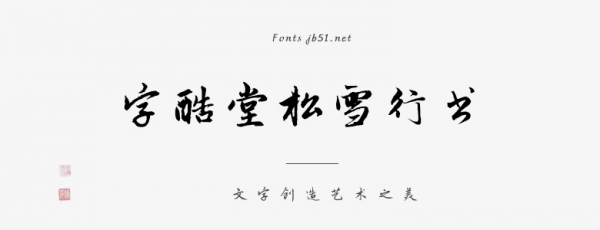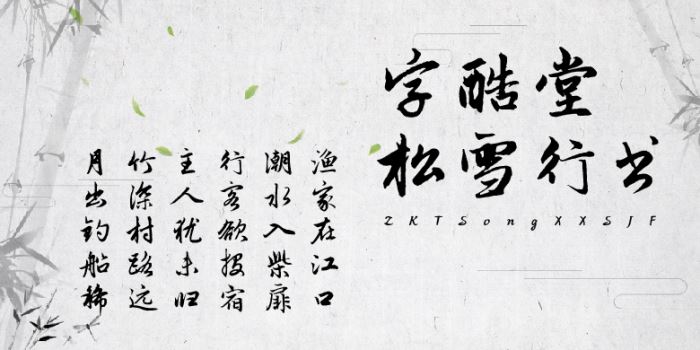
字酷堂松雪行书
字酷堂松雪行书由方正字库过中运设计师出品的艺术字体,该字源自元代书法家赵孟頫的行书书法作品,并根据其书风补上了缺字及简体部分,,适合应用于艺术设计、平面宣传设计、网页设计,书法等领域。
字体介绍
字体源自元代书法家赵孟頫的行书书法作品,并根据其书风补上了缺字及简体部分,赵孟頫博学多才,能诗善文,工书法,精绘艺,擅金石,通律吕,解鉴赏,尤其以书法和绘画的成就最高。在绘画上,他开创元代新画风,被称为“元人冠冕”;赵孟頫亦善篆、隶、真、行、草书,尤以楷、行书著称于世。其书风遒媚、秀逸,结体严整、笔法圆熟,创“赵体”书,与欧阳询、颜真卿、柳公权并称“楷书四大家”。。